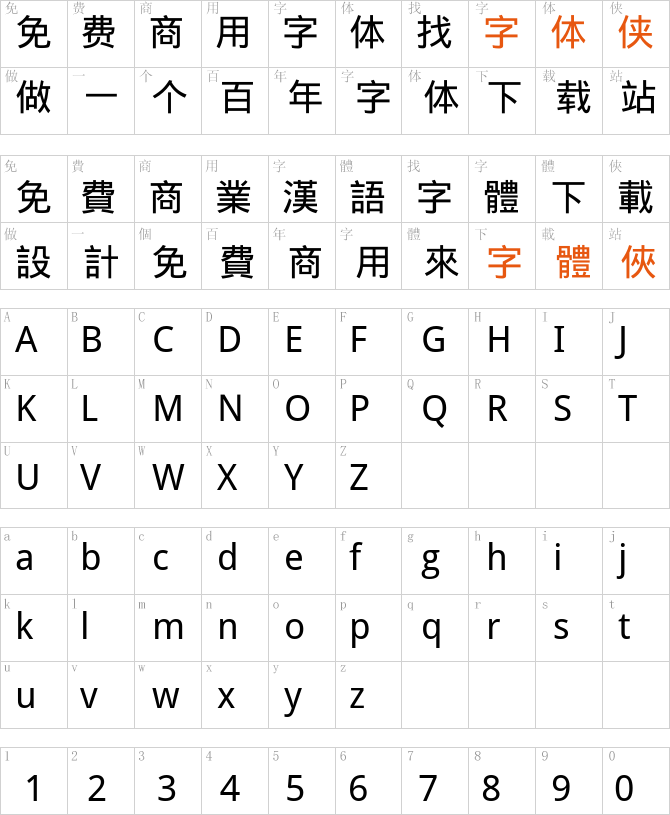
文泉驿微米黑字体,Google Droid的开源衍生字体。开彼源兮,斯流永继。
文泉驿微米黑字体缩略图:
文泉驿微米黑字体简介:
文泉驿微米黑是一款风格比较严谨的字体,与等宽正黑相比笔画更粗,也属于较为标准的黑体。笔触更加棱角分明,属于端正大方型的,适用于广告设计、平面杂志、书籍出版、包装印刷等文字要求较严谨的行业。文泉驿微米黑是一个"自由字体"。该字体包含了所有常用简体中文、繁体中文所需要的汉字(最新版本包含超过20932个汉字,完整覆盖GB2312/Big5以及GBK标准字符集)。该字体同时还包含了日文、韩文和其他几十种语言符号。以外,该字体还包含了高质量的Droid Sans拉丁符号和Droid Sans Mono等宽字体,并内置Hinting和Kerning信息。微米黑字体文件极小,特别使用于便携式电脑设备。